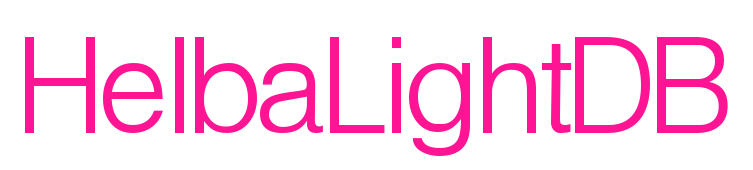
HelbaLightDB 詳情頁(yè)
HelbaLightDB字體字庫(kù)是一款讓人賞心悅目、百看不厭的英文字體,適合各類廣告和產(chǎn)品包裝設(shè)計(jì)應(yīng)用,字體大小0.04MB,格式為ttf字體,上傳用戶是金百誠(chéng),作者/版權(quán)方為未知